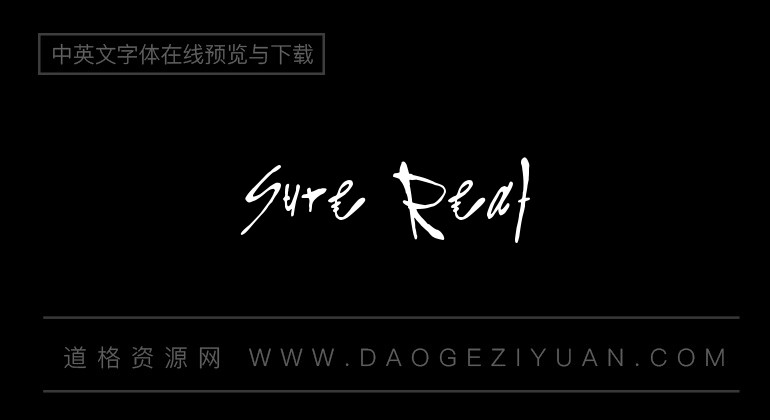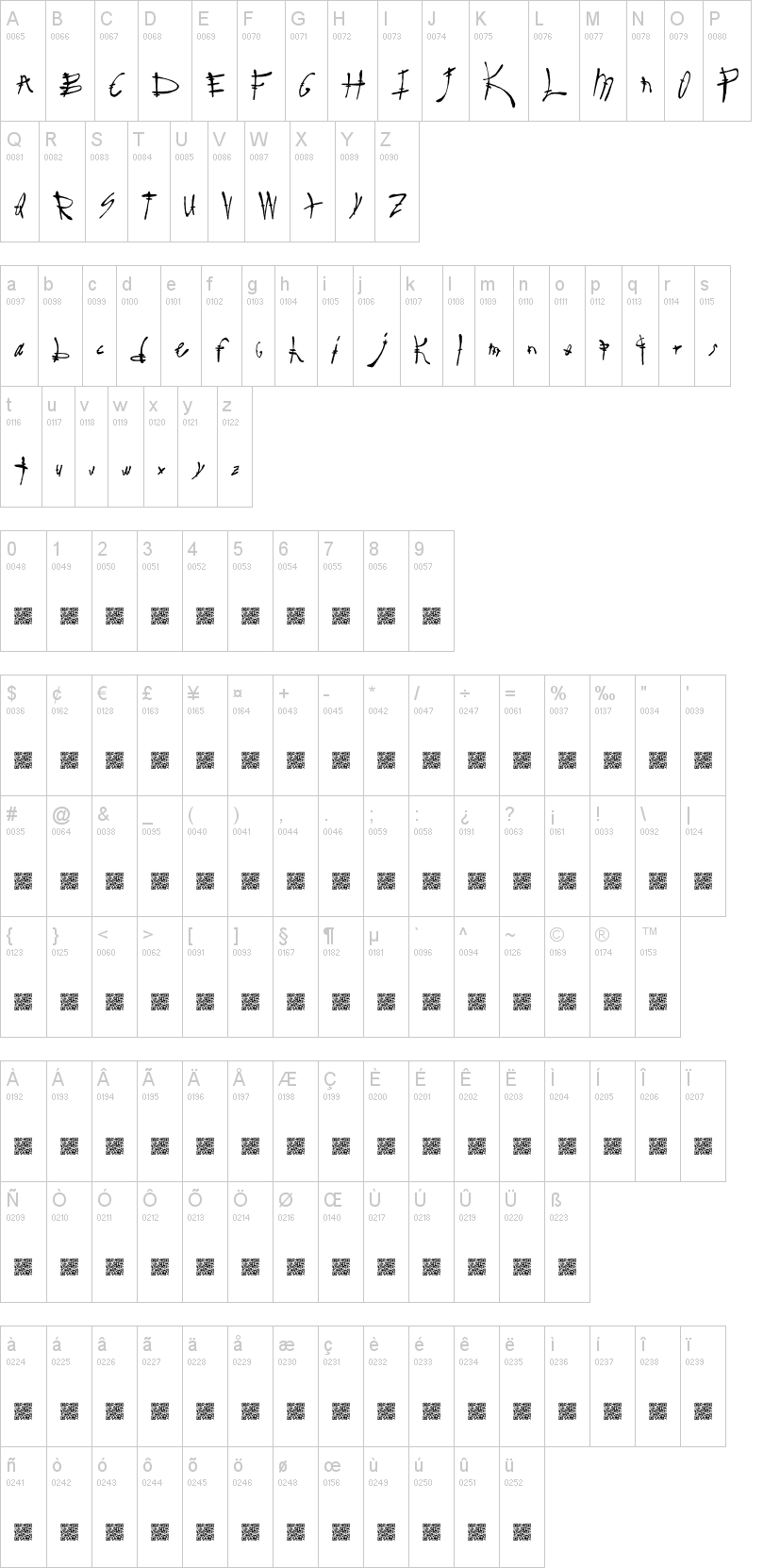
Sure Real 是一款新字体,由著名的西班牙字体设计师Juanjo López所设计,它是一款现代化的字体,具有独特的视觉效果,能够有效地提升文字的表达力。它有着流畅的线条,让文字看起来更加清晰,更具有表现力。它的字体重量可以根据需要进行调整,从而满足不同的需求,并且它的字体可以在多种平台上使用,比如:网页、报纸和书籍等。内容介绍
Sure Real是一款非常不错的手写艺术字体,具有很好的视觉感,适合于文化类的宣传设计、商业类品牌的广告和产品包装设计以及个性化文字排版等较多场景。